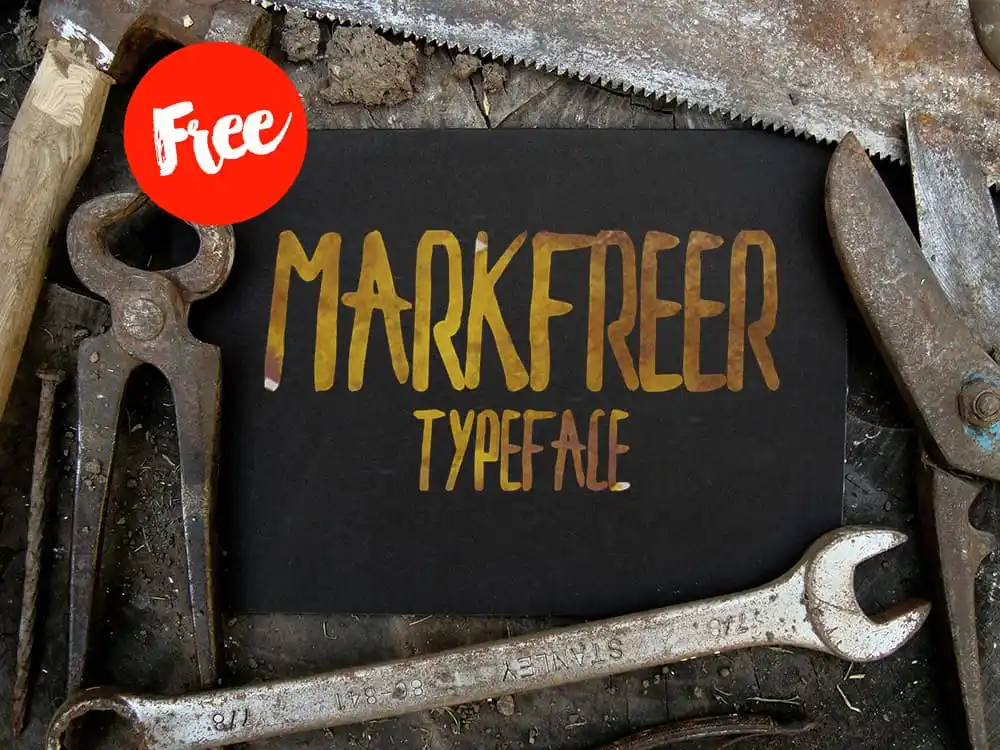
Markfreer Typeface – Fonte Grátis
Markfreer Typeface
A Markfreer Typeface é uma fonte à mão livre criada por Hamilton que oferece uma experiência única e autêntica no design tipográfico. Este projeto é inspirado pela arte handwritten de Esquerrà, um autor espanhol respeitado na indústria do design gráfico. A Markfreer é conhecida por sua personalidade sólida e seu estilo distintivo, que oferece uma opção diferenciada para designers e criadores de conteúdo. Se você está procurando uma fonte à mão livre única com um charme sofisticado, a Markfreer Typeface definitivamente vale a pena ser considerada. Descarregue-a agora e experimente sua versão livre, sem comprometer a qualidade ou o design impecável dessa fonte elegante.